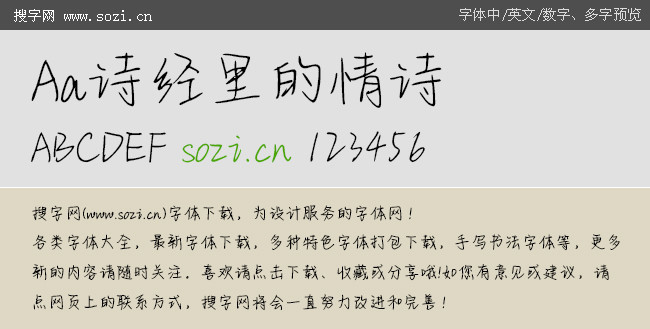
Aa詩經(jīng)里的情詩
搜字網(wǎng)給大家提供一款A(yù)a詩經(jīng)里的情詩中文字體下載,這是一款手寫風(fēng)格的書法字體,字體流暢,效果秀麗,適合海報(bào)設(shè)計(jì)、畫冊等宣傳廣告等應(yīng)用(此字體為個(gè)人非商用版,如需商用請聯(lián)系作者購買版權(quán))。